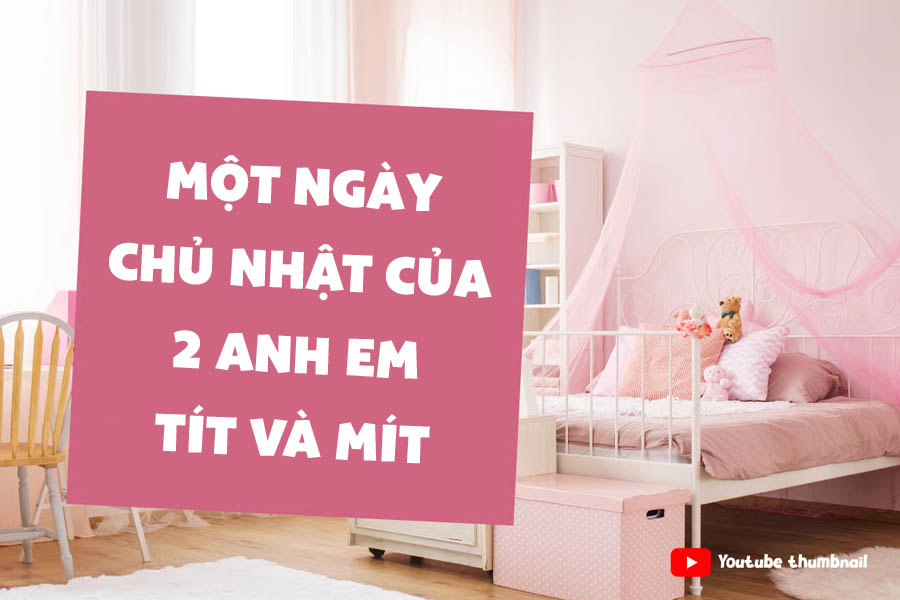
Phông chữ hoạt hình miễn phí SVN Bango
SVN-Bango là một font chữ tiêu đề mạnh mẽ và nổi bật, được Việt hóa bởi SVN. Font được phát triển từ bản gốc Bango do T-26 Studio thiết kế, mang phong cách retro kết hợp hiện đại, với cấu trúc chữ in hoa độc đáo, đậm chất hình học và nghệ thuật đương đại.
Không chỉ phù hợp cho các thiết kế mang tính thương hiệu, SVN-Bango còn là một font chữ hoạt hình lý tưởng. Các nét cong táo bạo và bố cục chữ vui nhộn khiến font dễ dàng ứng dụng trong các dự án sáng tạo như: tiêu đề game, poster hoạt hình, ấn phẩm dành cho trẻ em hoặc video giải trí. Đây là lựa chọn lý tưởng nếu bạn đang cần một font chữ cho thiết kế vui nhộn, tràn đầy năng lượng và không kém phần cá tính.
Font hỗ trợ đầy đủ tiếng Việt, chuẩn Unicode, được Việt hóa chỉn chu bởi SVN, đảm bảo hiển thị đẹp, không lỗi dấu trong mọi ngữ cảnh sử dụng.
Nếu bạn đang tìm kiếm một font chữ Việt hóa mạnh mẽ, vừa mang phong cách retro, vừa phù hợp với các dự án hoạt hình, vui nhộn, thì SVN-Bango chính là sự lựa chọn hoàn hảo dành cho bạn.